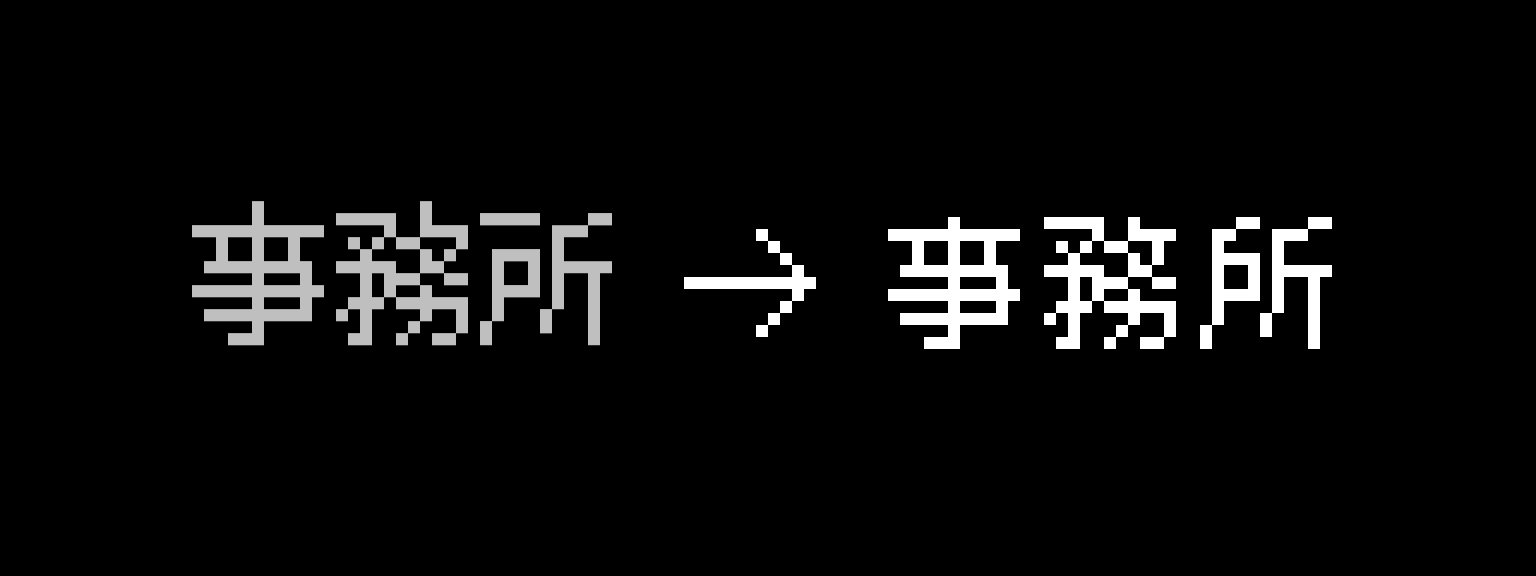
俐方体11是基于M⁺goic 12r衍生的开源繁体中文11×11点阵字体,可用于创意风格的游戏以及算法原型。
收录字数:常用国字标准字体 4808 字;Big5第一字面5401;IICore 台湾常用字 T1A、T2A 及部分 T2B;台客闽粤字;注音符号;GB 2312 Level-1;通用规范汉字表 一级;元素周期表之所有元素符号。
本字型以日文字型 M⁺ gothic 12r 为基础替繁体中文进行修改与扩充,其中包括适用繁体中文的标点符号以及较符合台湾地区习惯的字形等。